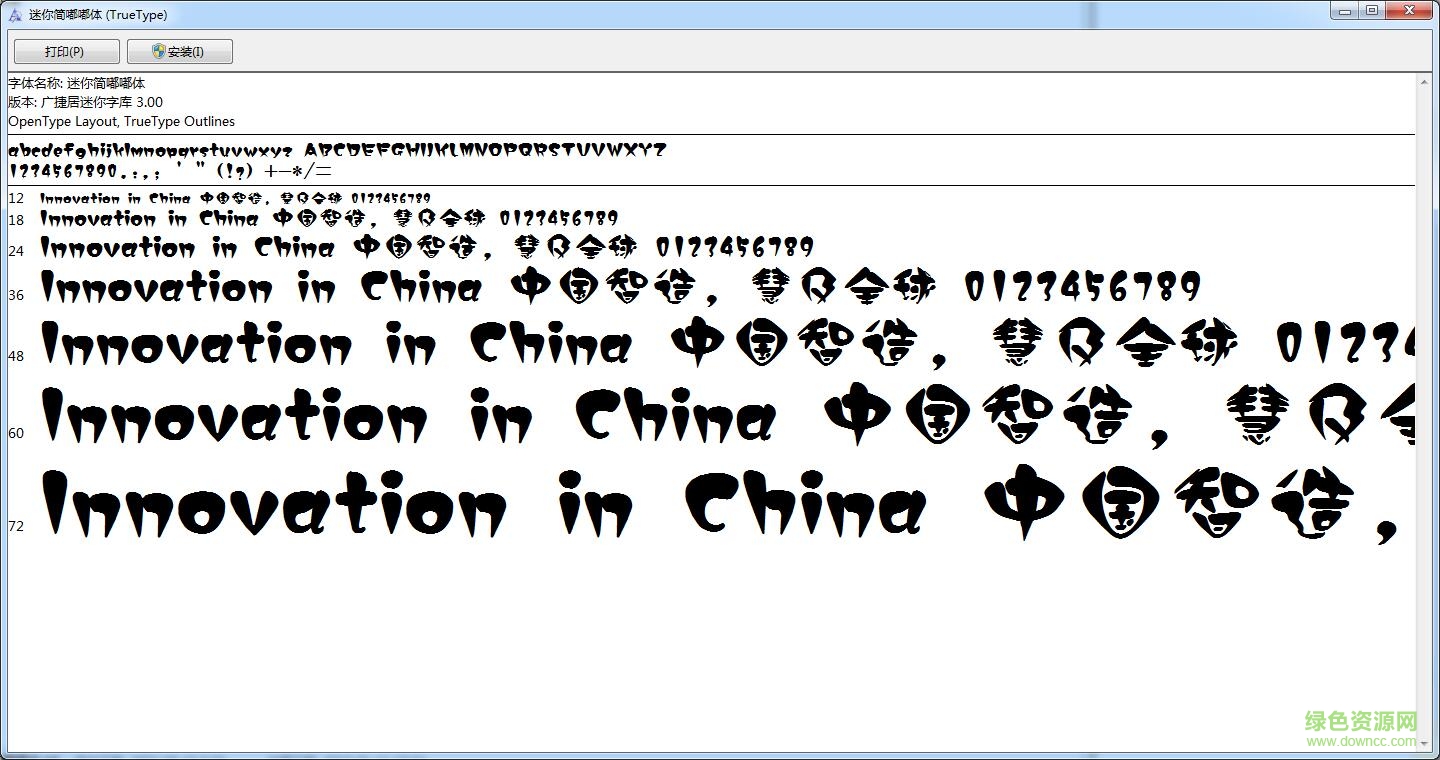
迷你簡(jiǎn)嘟嘟字體是一套免費(fèi)的字體應(yīng)用!這款字體適用范圍非常廣泛!常被用于圖像設(shè)計(jì)、制作工程圖等,這款字體最大的特點(diǎn)是字體中較少見(jiàn)的中英雙語(yǔ)字體,喜歡的朋友快來(lái)下載吧!
迷你簡(jiǎn)嘟嘟體是一款字形效果獨(dú)特的中英文雙語(yǔ)字體的。它將漢字上面部分方正的筆畫轉(zhuǎn)折處理為更圓潤(rùn)的筆畫,大小粗細(xì)相同,十分美觀。該款字體非常適合印刷的朋友使用,字體適用于圖形圖像設(shè)計(jì)、電腦切割、動(dòng)畫創(chuàng)作、工程制圖、高精度專業(yè)等行業(yè)。需要的用戶歡迎在綠色資源網(wǎng)下載使用!
2.大小粗細(xì)相同
3.屬于中英文雙語(yǔ)字體